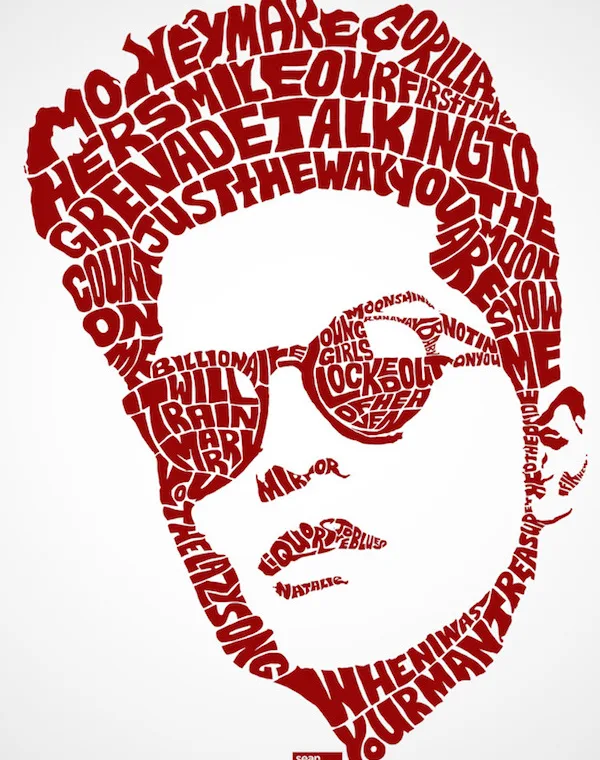
Ilustrador se inspira na cultura pop e cria fotos com tipografias personalizadas
O ilustrador e diretor de criação canadense Sean Williams faz fotos de celebridades utilizando apenas tipografia personalizadas por ele mesmo.
Ele ilustra a mão e usa textos dos títulos de filmes, letras de musicas para deixar um resultado bem semelhante ao artista inspirado, atualmente ele se inspira em diversos artistas como Beyoncé, Cher, Bruce lee, Bruno Mars e outros artistas da cultura pop.
O trabalho de Sean começou como um projeto pessoal e logo foi reconhecido, hoje ele trabalha com marcar internacionais em diversos projetos.